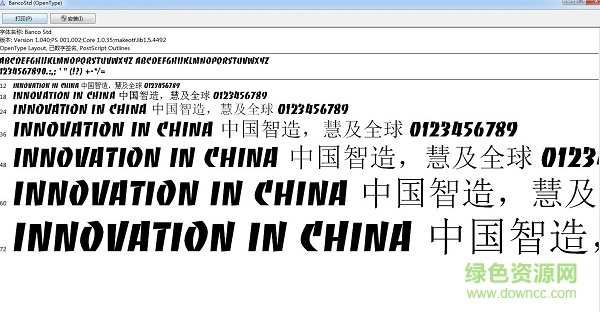
banco std字體是一款極具個(gè)性的英文海報(bào)字體,筆劃堅(jiān)實(shí),撇捺舒展,結(jié)體飽滿醒目,號(hào)召力強(qiáng),排版或設(shè)計(jì)效果俱佳,具有較強(qiáng)的動(dòng)勢(shì)美感,歡迎大家在綠色資源網(wǎng)免費(fèi)下載!